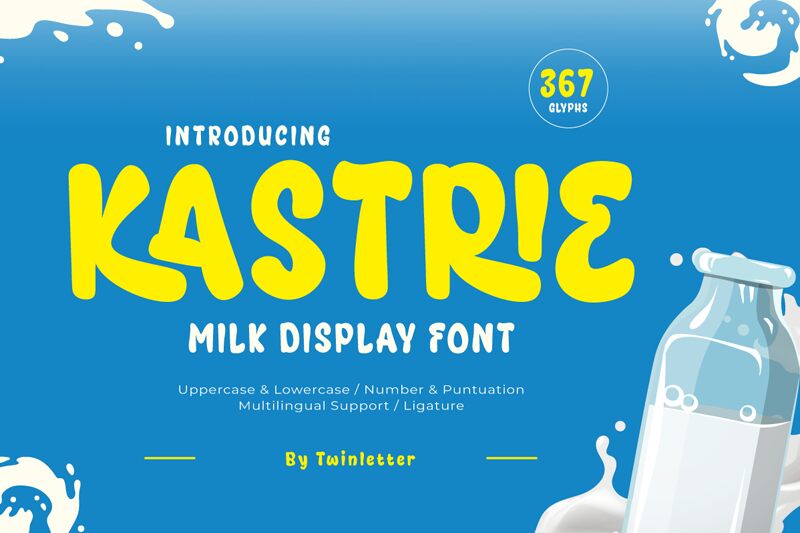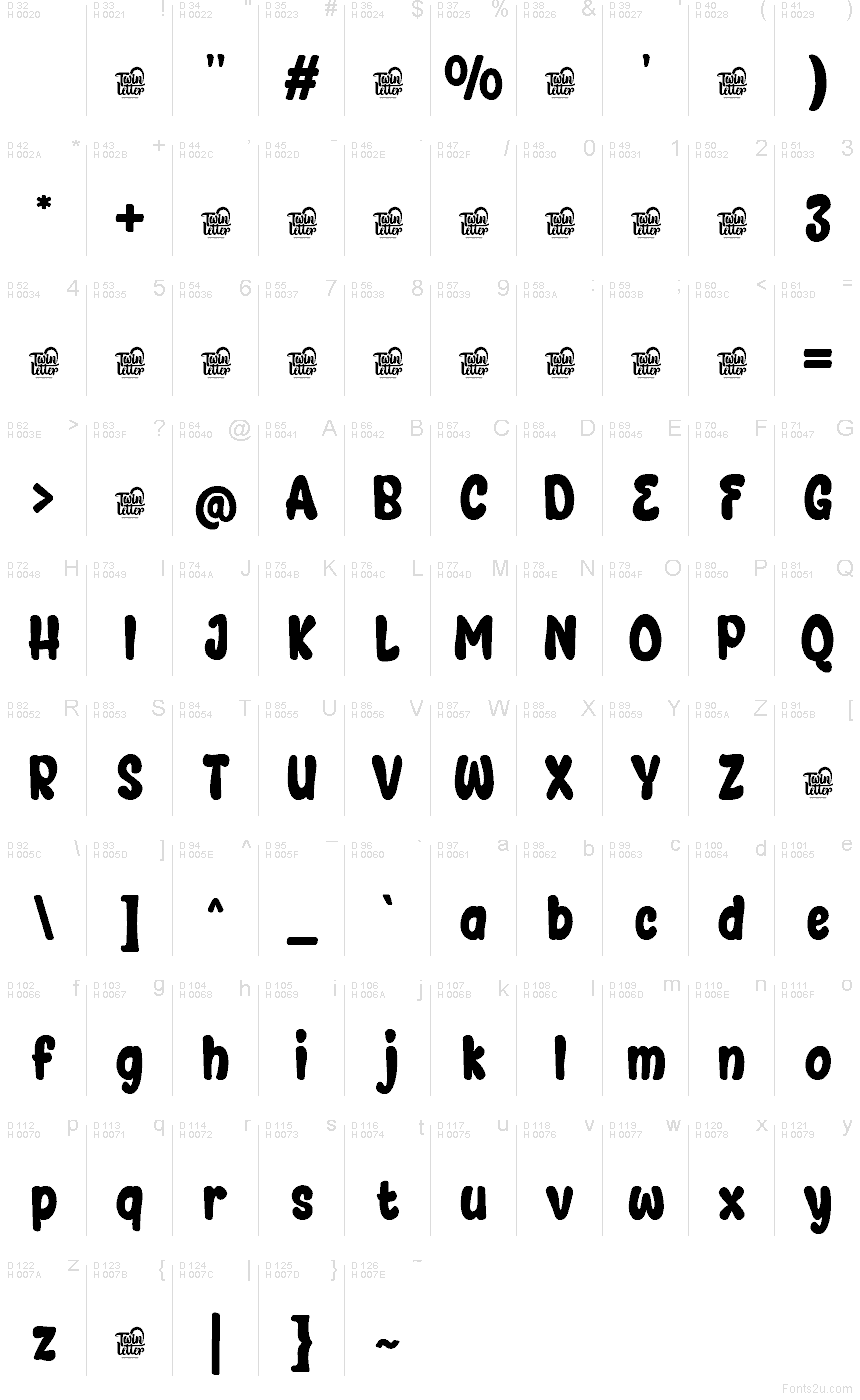
Kastrie von Twinletter ist eine kostenlose Cartoon-Displayschrift mit prallen, locker gezeichneten Buchstaben und einem unbeschwerten Comic-Charakter. Ihre ungleichmäßigen Breiten und weichen, bauchigen Rundungen verleihen der Schrift lebendige Frische.
Kinderbuchcover bieten ein natürliches Umfeld für diese sympathischen Formen, und der ungezwungene Humor passt ebenso gut zu Snackverpackungen, Partyplakaten und animierten Titelkarten. In solchen Umgebungen können die abgerundeten Silhouetten Teil eines fröhlichen Produktdesigns werden und eher an Maskottchen, Sticker und einfache Charakterillustrationen erinnern, als bloß wie neutraler Fließtext zu wirken.